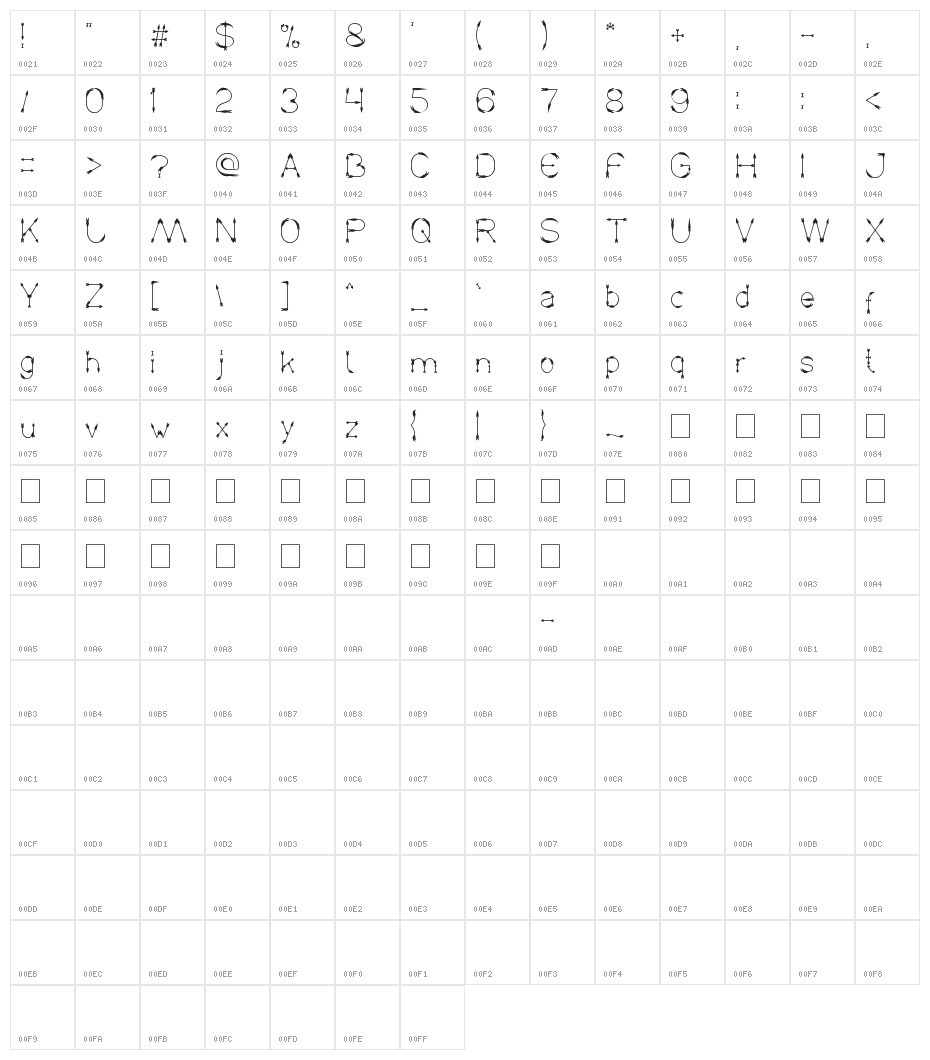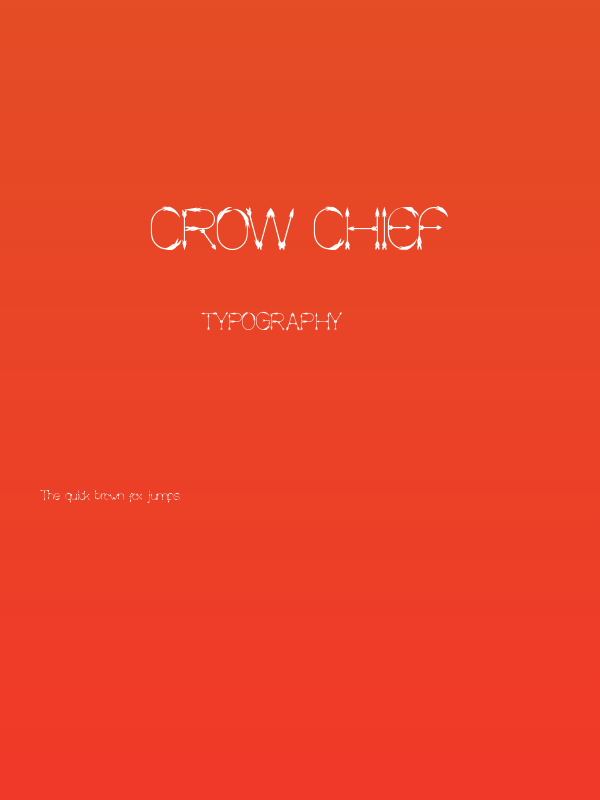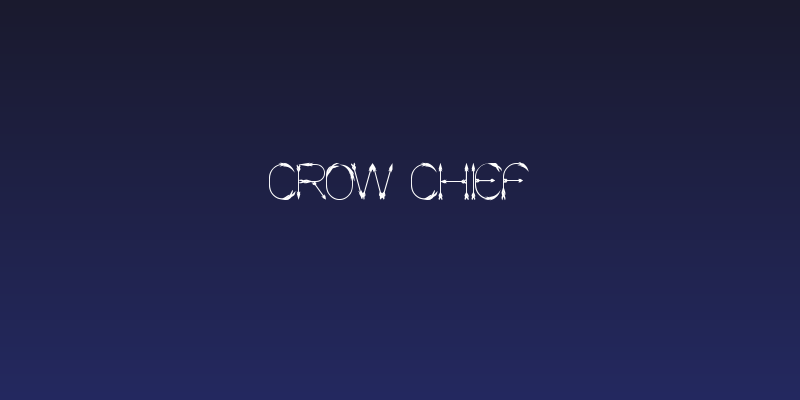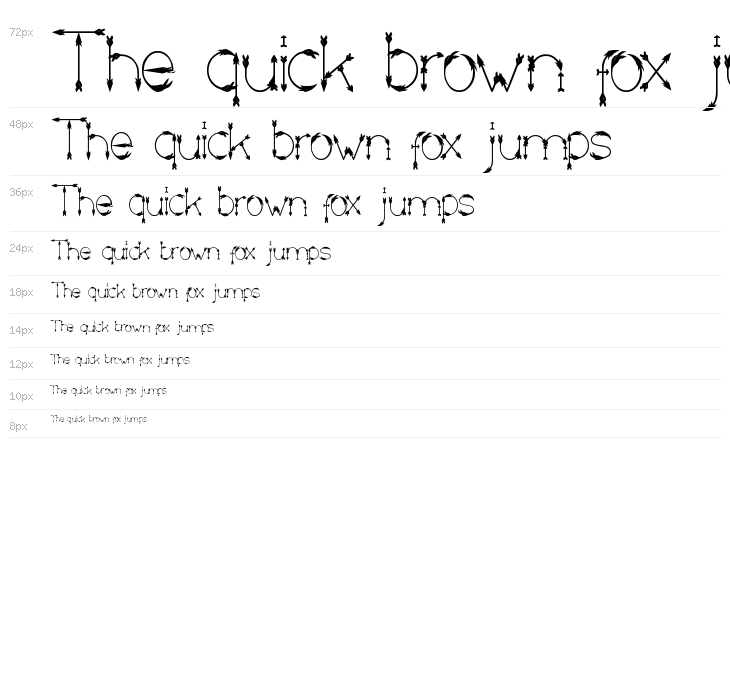
Crow Chief Font
| Projetos propostos | Ideal for themed posters, event invitations, branding for outdoor or adventure-related businesses, and any project seeking a bold, thematic design. |